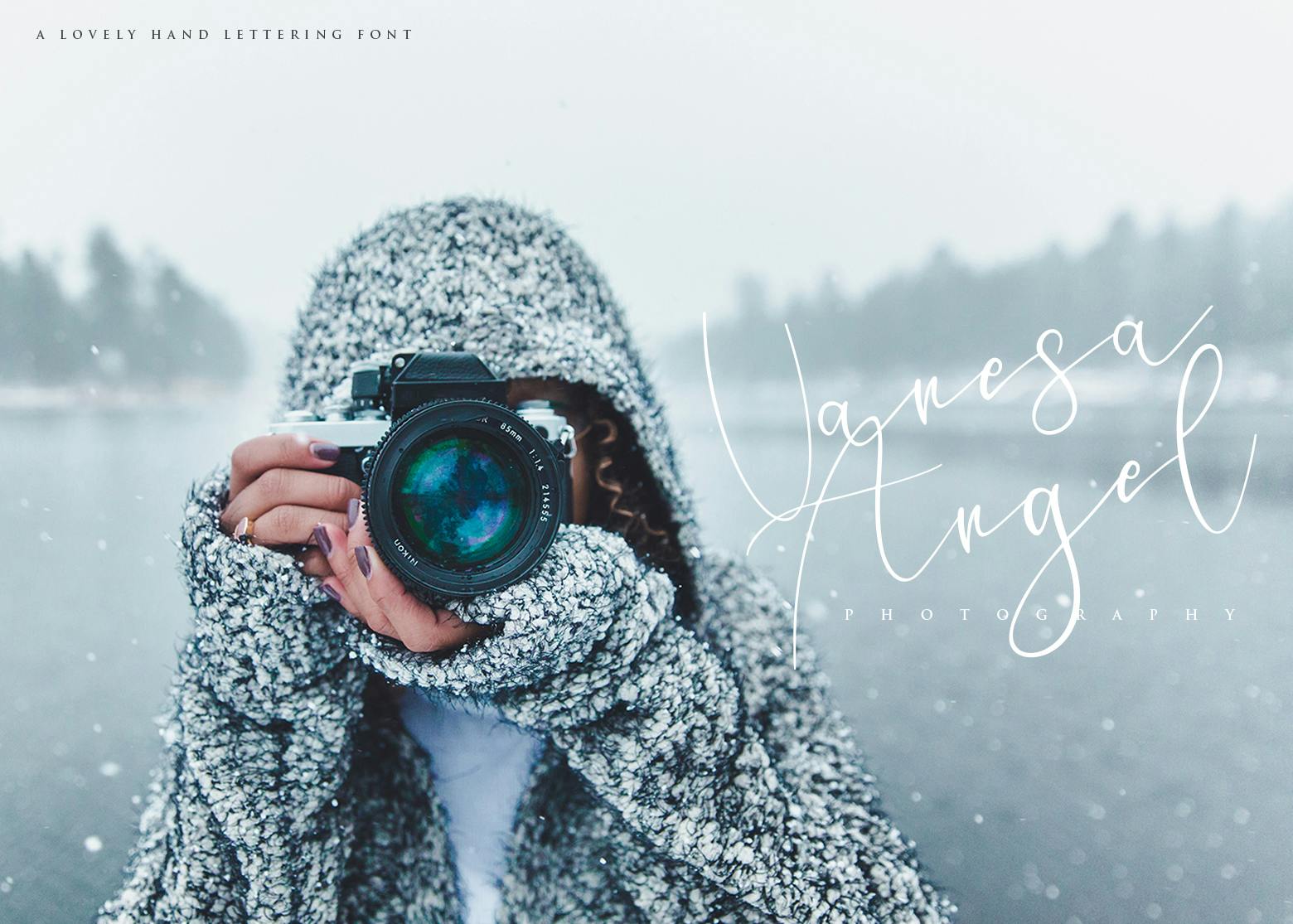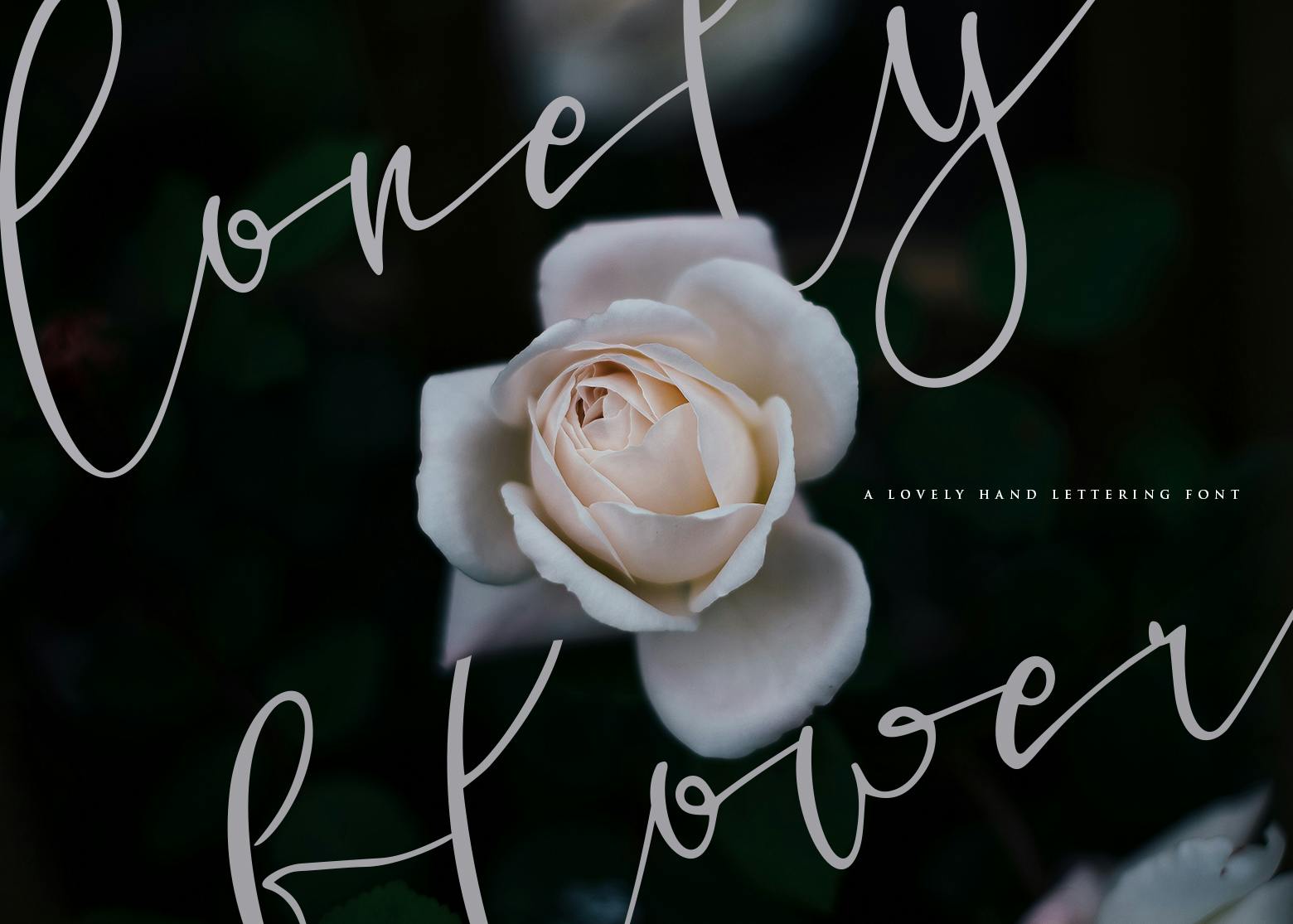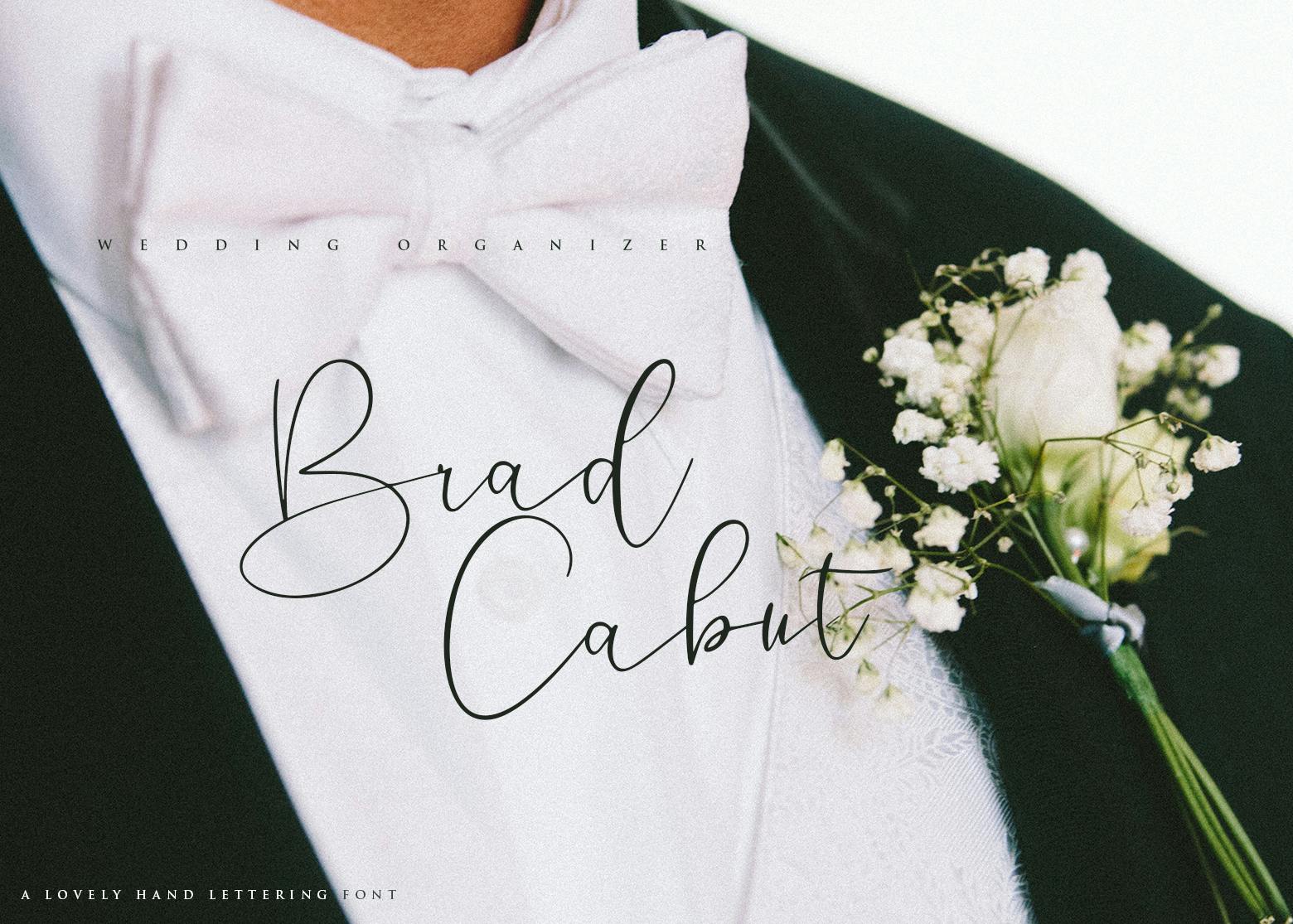
Santoy - فونت دستنویس با سبک خطاطی، بسیار زیبا برای طراحی کارتهای دعوت، مواد برندینگ، کارتهای ویزیت، نقلقولها، پوسترها و موارد دیگر!
کاراکترهای جایگزین به چندین ویژگی Open Type تقسیم شدهاند، از جمله مجموعههای سبک، جایگزینهای متنی، SWASH و Ligature. ویژگیهای Open Type را میتوان با استفاده از برنامههای حرفهای مانند Adobe Illustrator، Adobe InDesign، Adobe Photoshop، Corel Draw X و Microsoft Word دسترسی پیدا کرد. این فونت دارای کدگذاری PUA unicode است (فونتهای مخصوص کدگذاری شده) تا تمام کاراکترهای جایگزین بهراحتی و بهطور کامل قابل دسترسی باشند.